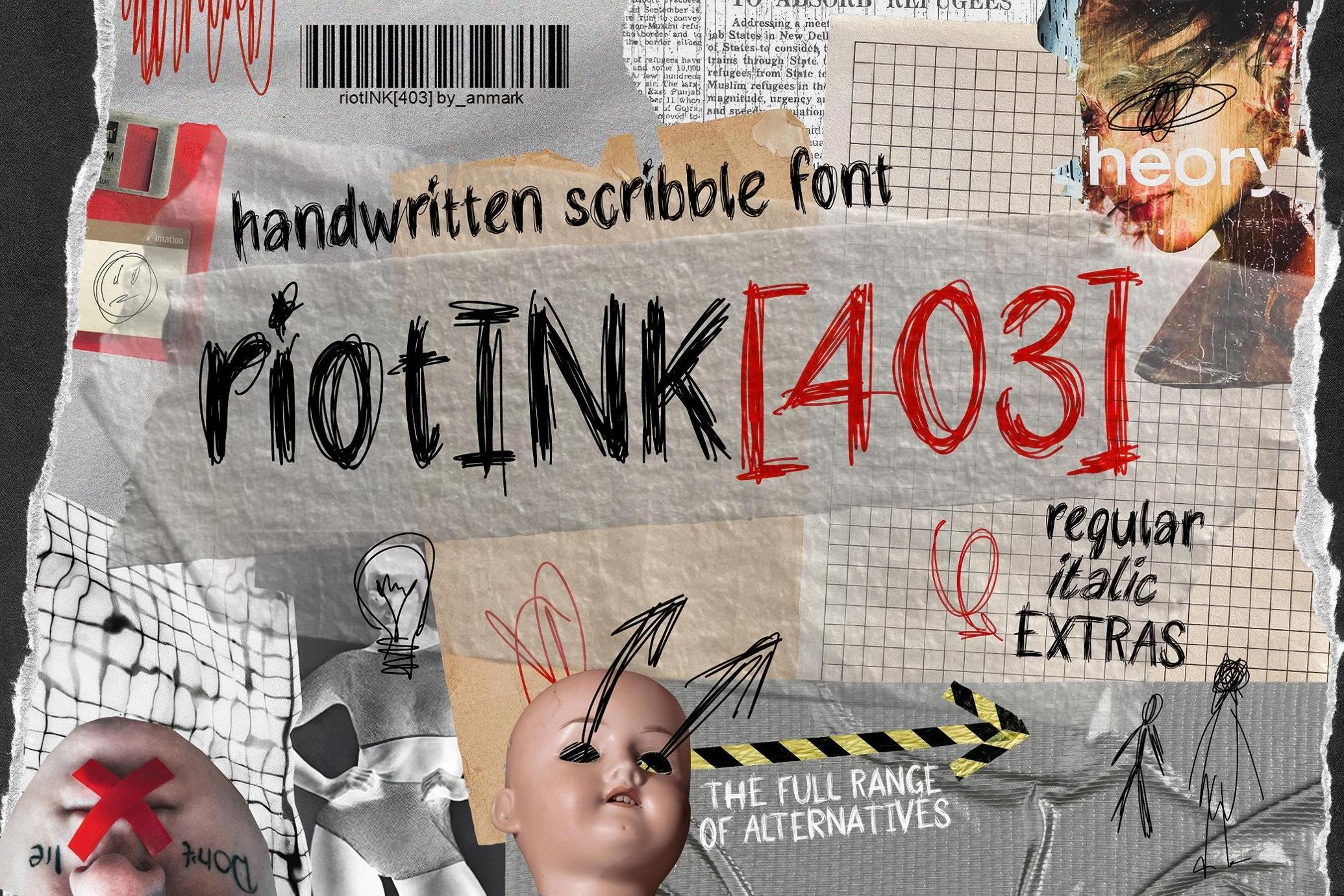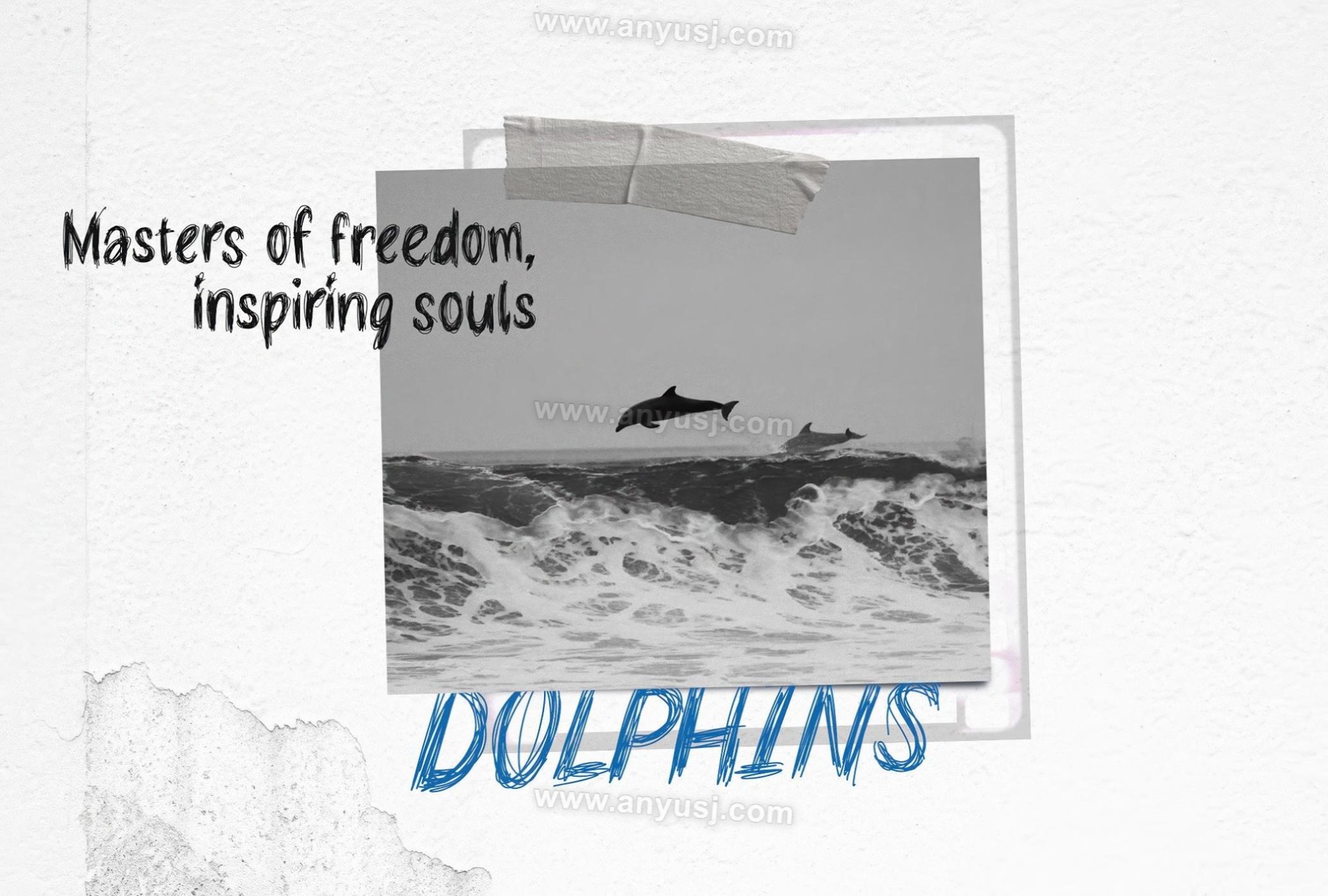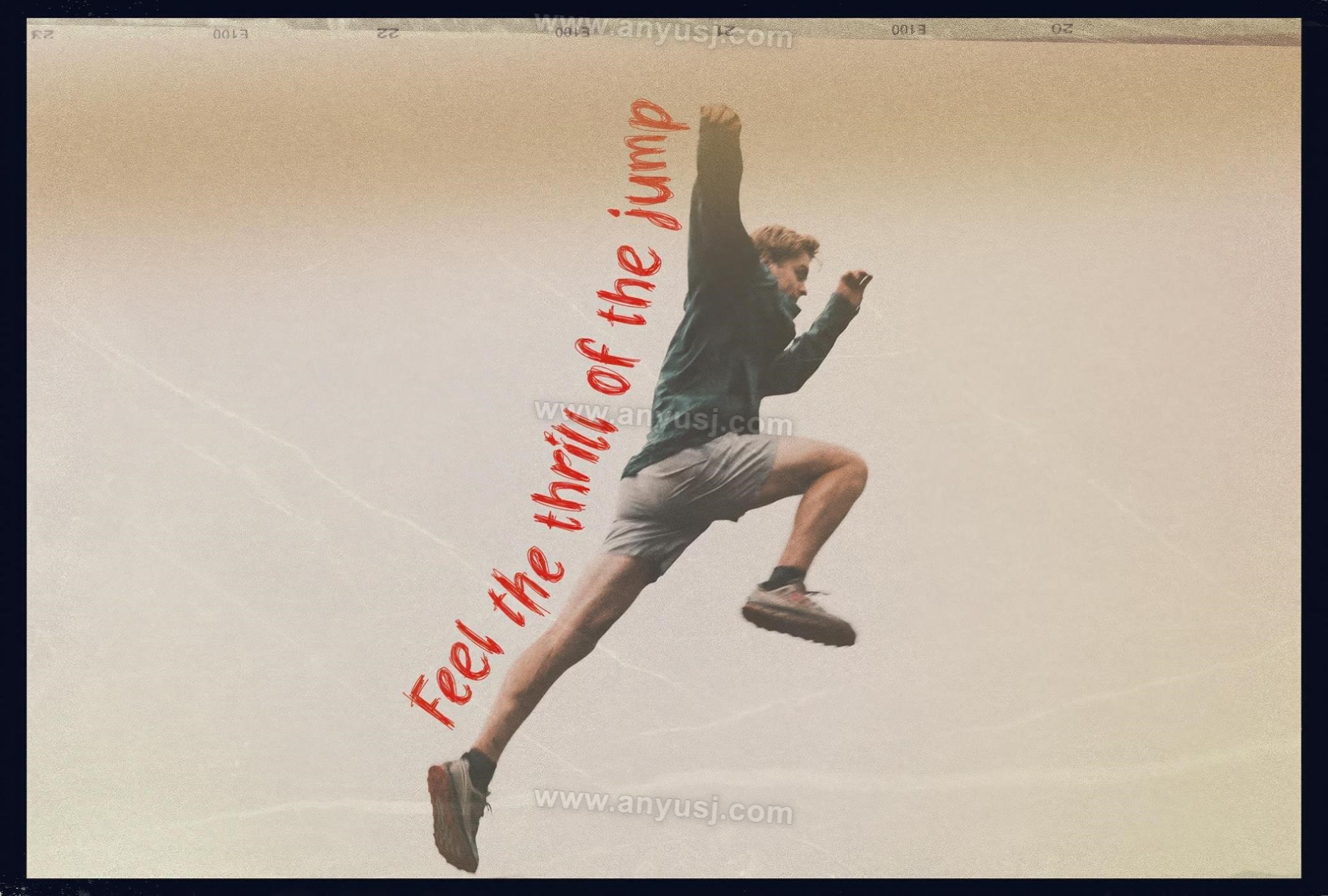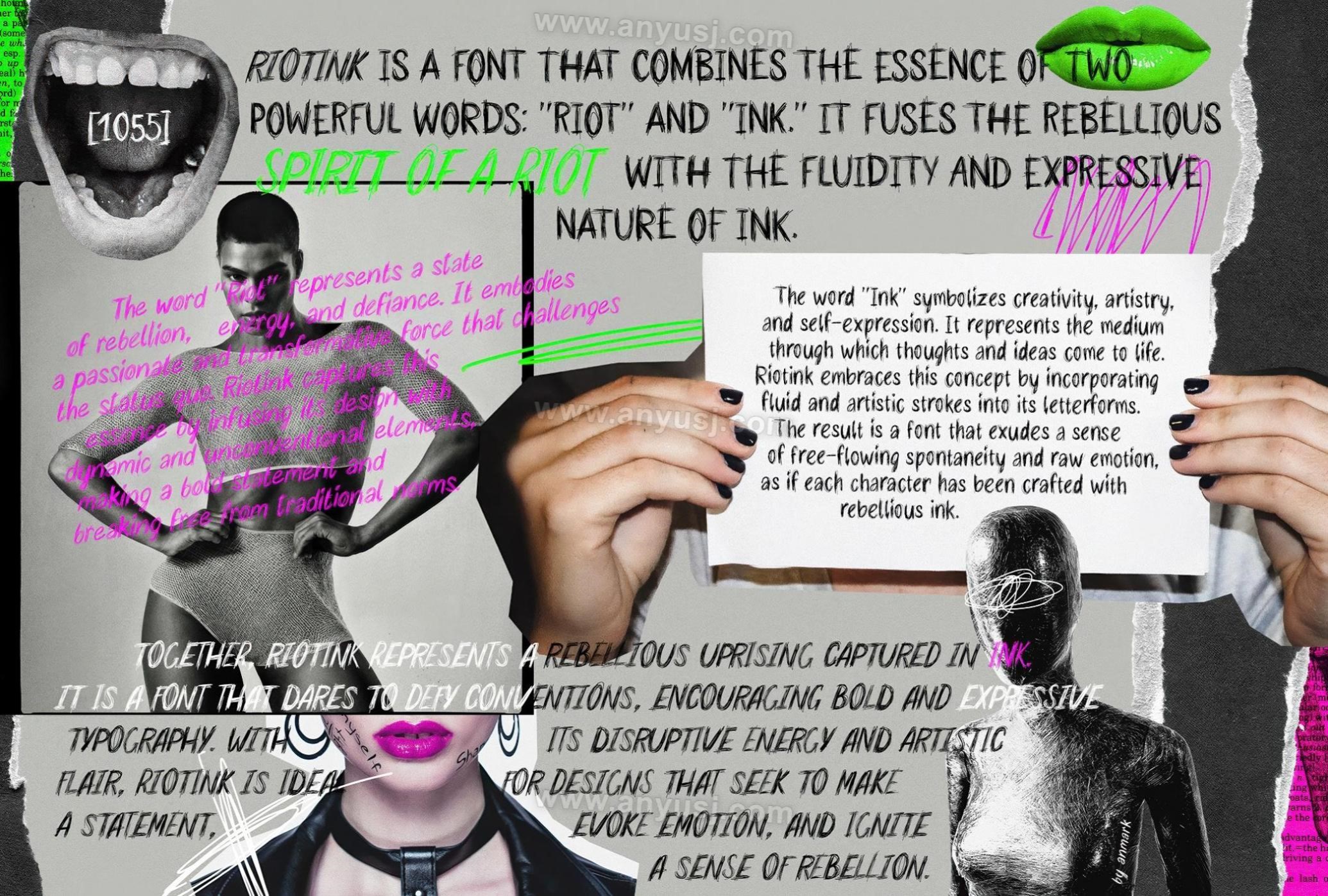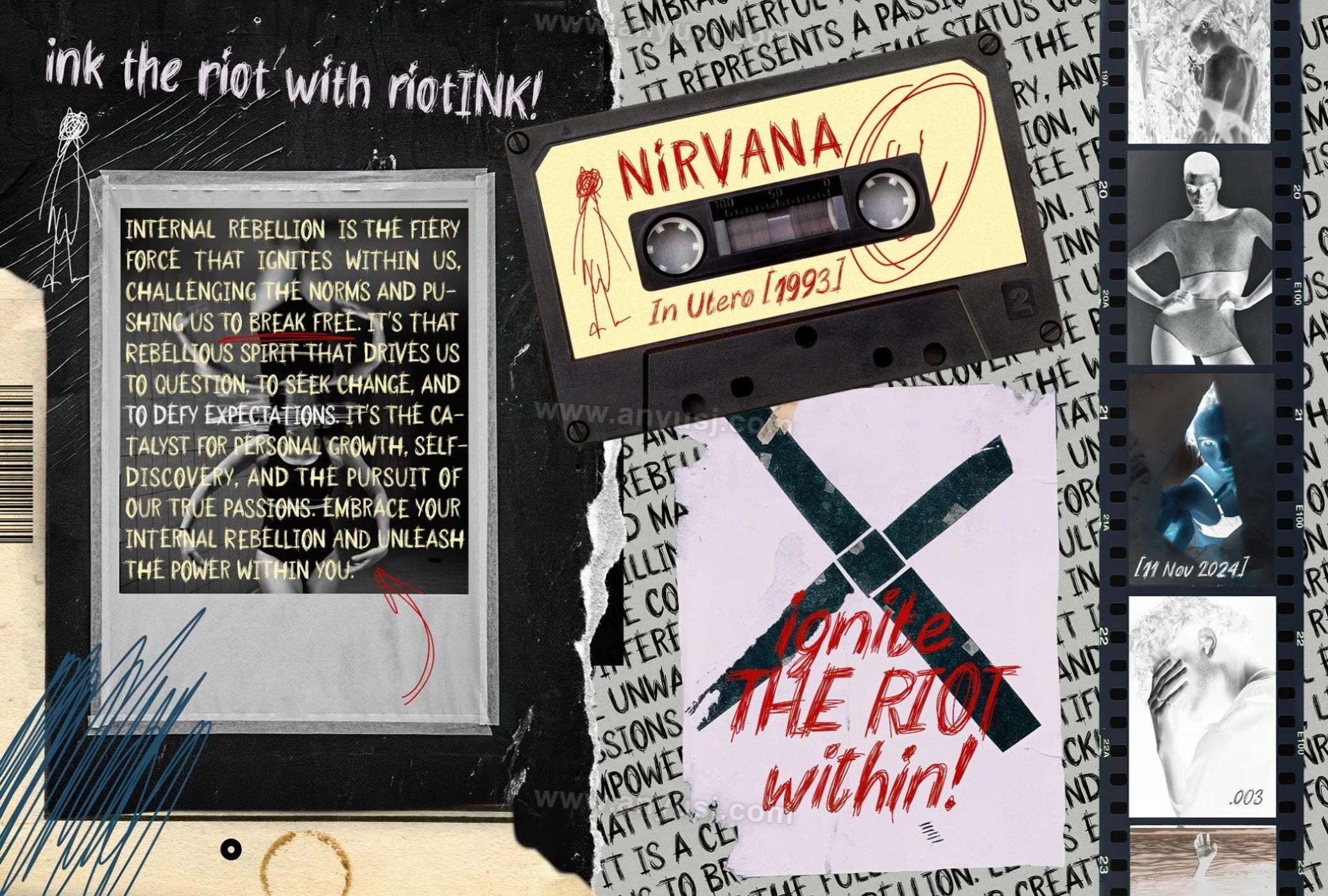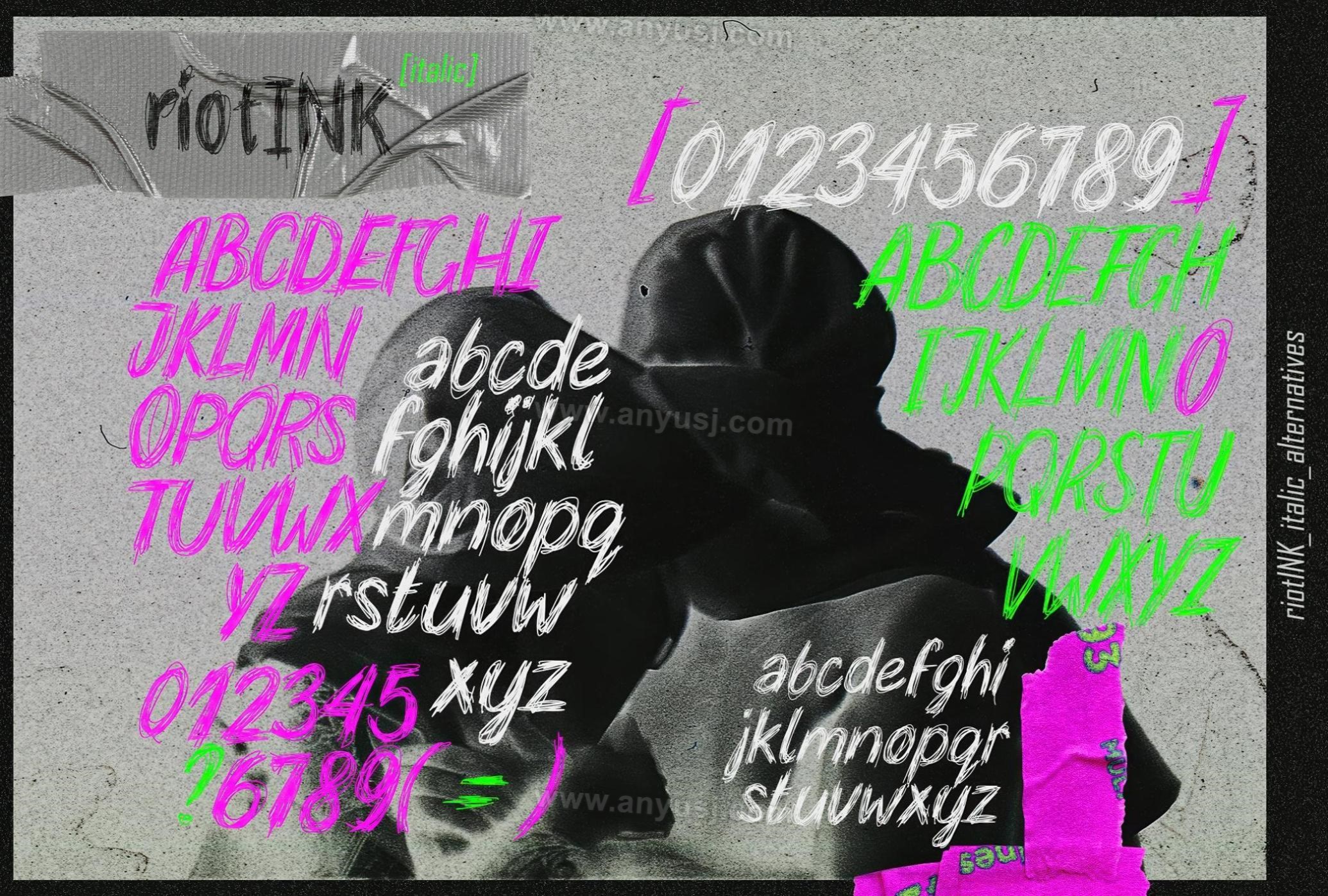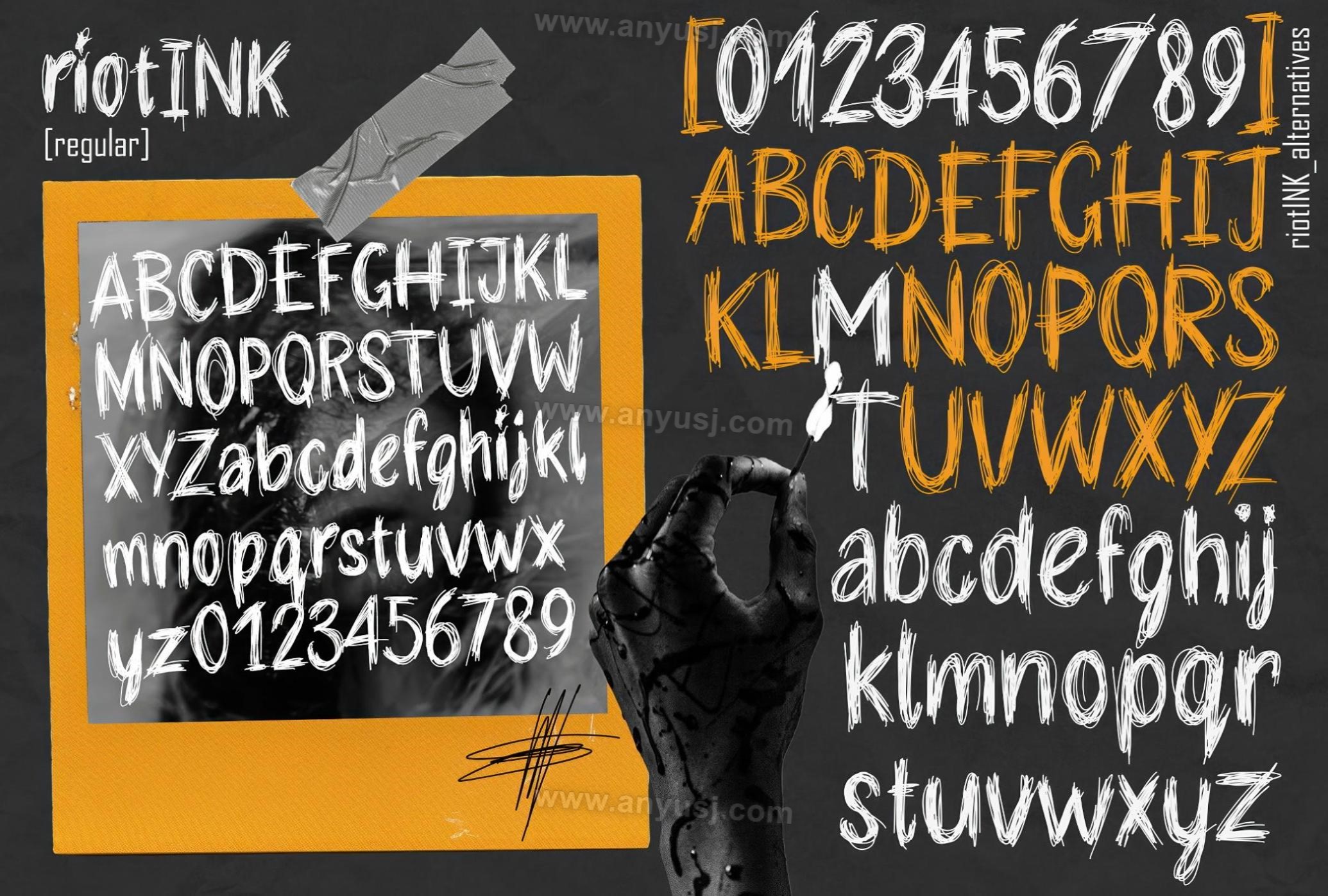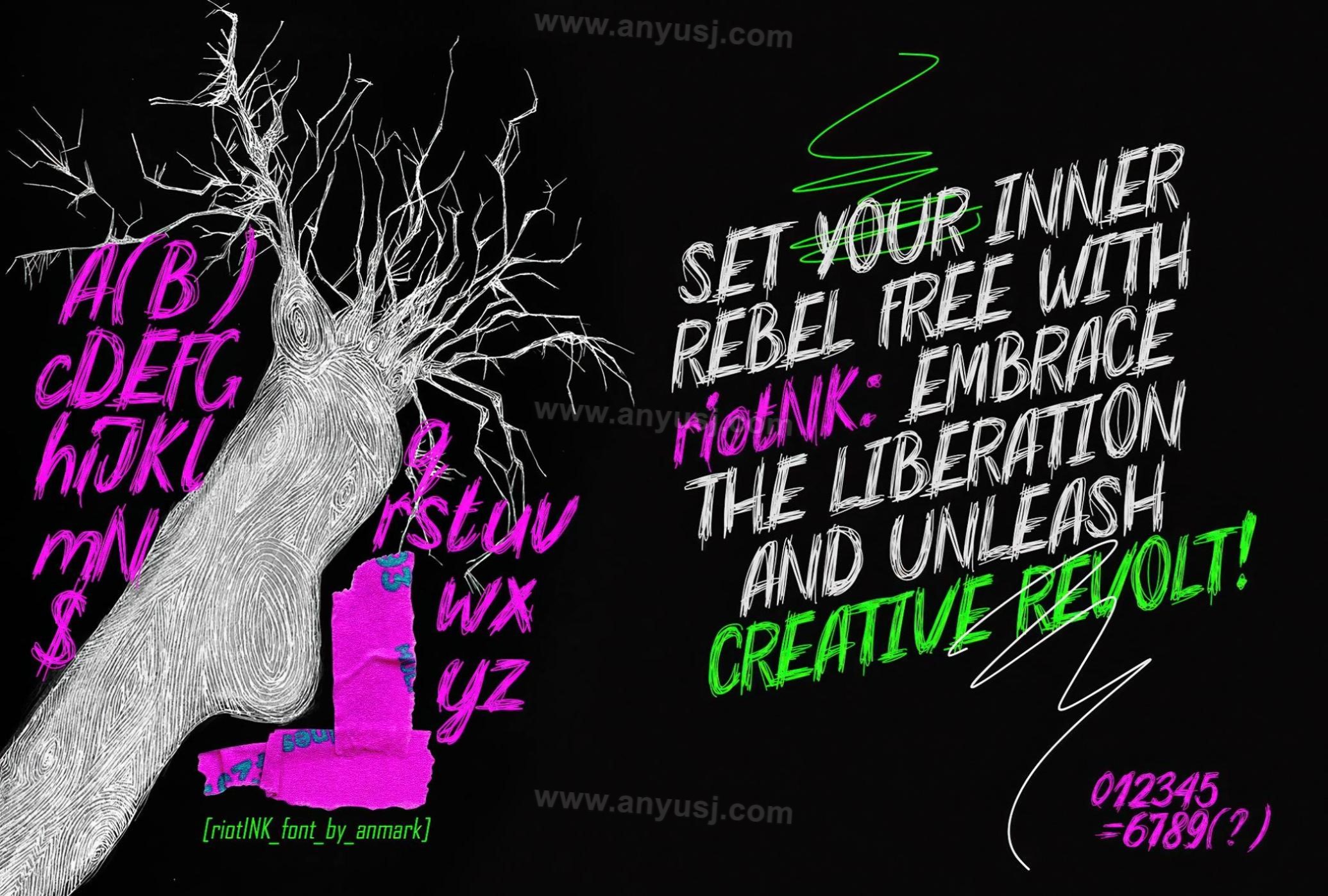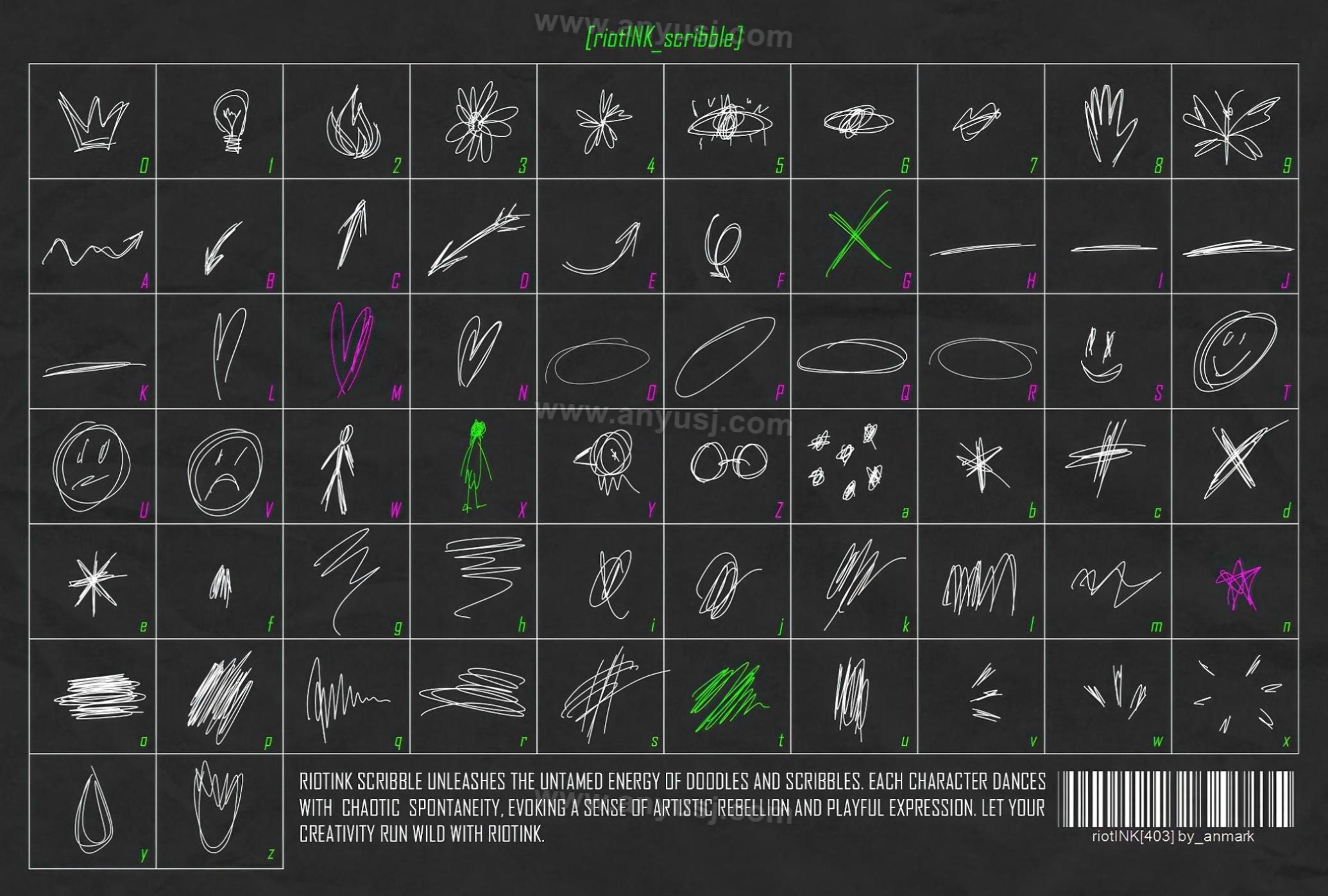
3款复古狂野街头涂鸦艺术手写装饰英文标题logo排版西文字体组合套装RiotINK. Handwritten Scribble Font
认识一下 RiotINK,这种字体看起来就像是踢开了传统排版的大门,在后面留下了一串沾满墨水的混乱。
RiotINK 咆哮着墨守成规,撕裂了简洁线条和完美曲线的单调。它潦草的混乱感觉就像在一个不安的夜晚从笔记本的边缘撕下来的。它有 3 种不同的样式:常规、斜体和狂野的涂鸦变体。 受到街头艺术的不可预测性和杂志文化的电脉冲的启发,这种字体将混乱变成了设计黄金。
常规和斜体版本的字形集非常标准—— 大写和小写字母、数字和标点符号。 但是当谈到涂鸦风格时,该套装只是用无政府主义的涂鸦撕碎了传统的字体,使该字体成为音乐专辑封面、邋遢的海报或具有 DIY 态度的非传统品牌的天赐之物。